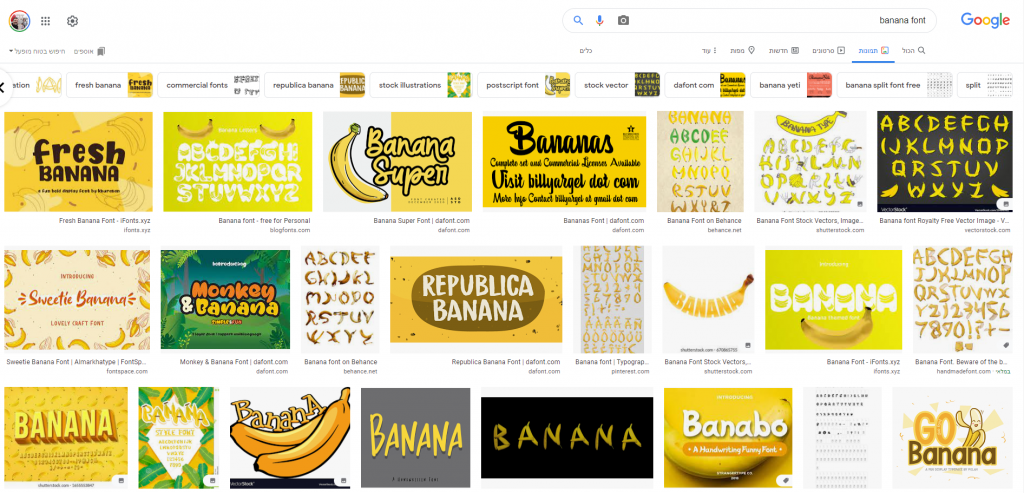
פונט בננה הוא פונט בסגנון קליל בצורה מעוגלת עם קווים.
מטרתו היא למשוך תשומת לב באופן שאי אפשר לפספס אותו.
גופן בננה נועד גם לעזור לאנשים דיסלקטים לקרוא ביתר קלות.
גופן הבננה ידוע במראה הייחודי שלו, הכולל את צורת האות הגדולה B.
הצורה נועדה להקל על הקריאה של הגופן בגדלים קטנים יותר.
זה הופך אותו לבחירה מצוינת עבור בלוגים או סוגים אחרים של כתיבה המשמשים באינטרנט כדי להפוך אותם לקריאה יותר.
פונט בננה
ישנן וריאציות רבות ושונות של גופן זה המשמשות למטרות שונות.
הפופולרית ביותר היא גרסת הסמיילי והיא נוצרה לשימוש בלוח הודעות שנקרא BBS (מערכת לוח מודעות).
האתר הראשון שהשתמש בגופן הבננה היה banana.com והוא הפך מהר יותר לפופולרי כתוצאה מכך.
גופן בננה זכה לפופולריות בקרב משתמשי האינטרנט והפך לאחד הפונטים הפופולריים ביותר בכל הזמנים.
גופן בננה משמש כמעט בכל סוג של פרויקט – דפוס, אינטרנט, גרפיקה, מוצרים וכו'.
לאיזה דברים כדאי לשים לב בשימוש בגופן זה?
כדאי לוודא שהעיצוב תואם את המסר שרוצים להעביר, יש אנשים שעשויים לחשוב שהפונט,
כיף או שובב בעוד שאחרים עשויים למצוא את הפונט מעצבן או ילדותי.